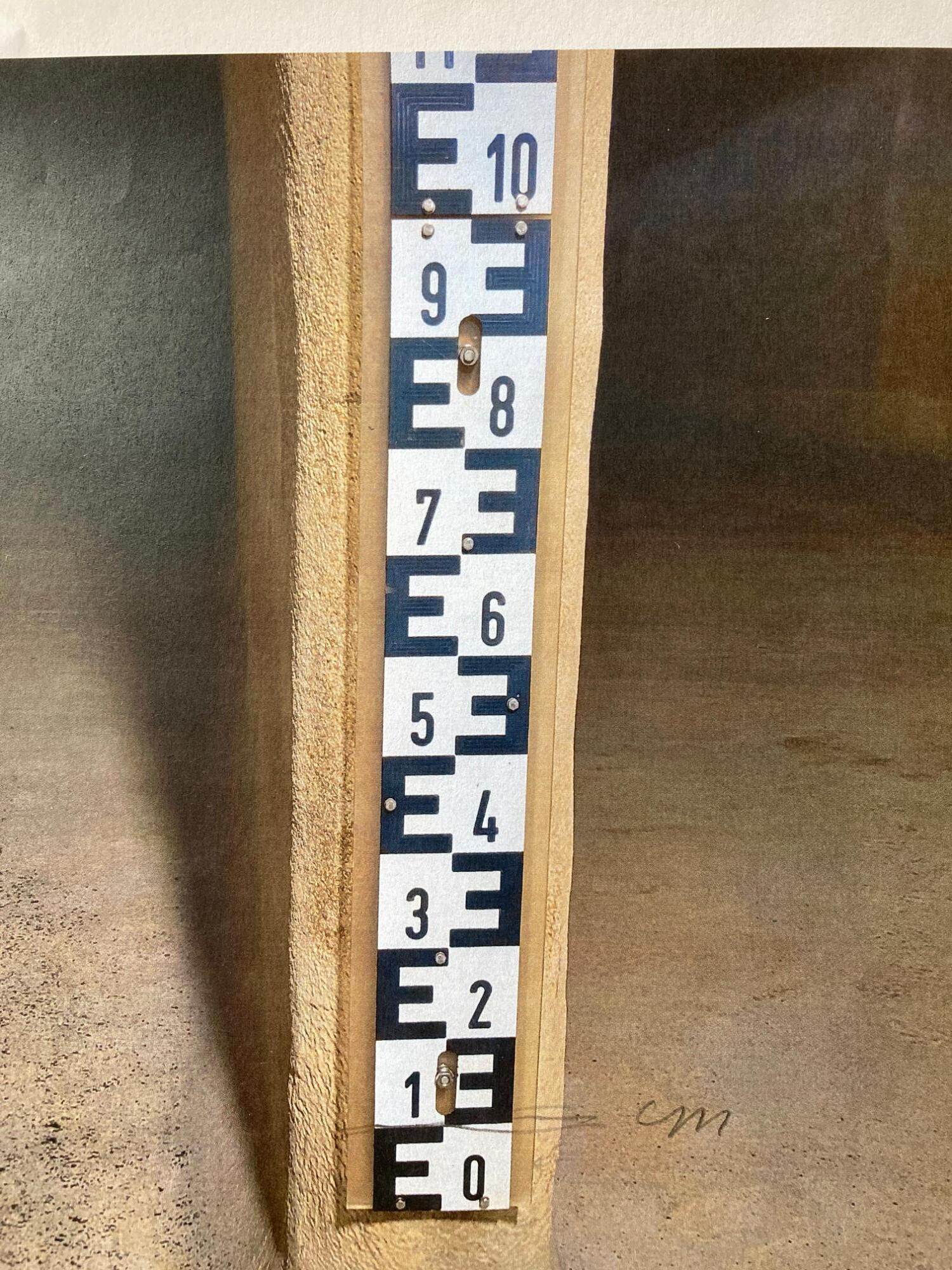
Pegellatte: Aus welcher Schrift stammen diese Zahlen?
Hallo. Für eine Ausstellung muss ich eine Pegellatte nachsetzen. Da die Latte im Kontext mit Bildern einer bestehenden Latte gezeigt wird, möchte ich unbedingt bei den Zahlen mit derselben Schrift arbeiten. Kann mir jemand sagen, wie diese Schrift heisst.
Danke, lieber Thomas. Ich bin eigentlich auch bei der DIN gelandet. Doch die "Endungen" der 6 und der 9 stimmen gar nicht überein und auch die "Abwärtsseite" der 1 scheint mir kürzer zu sein...
Es gibt in der DIN1451 für die 6 und 9 zwei verschiedene Formen. Mit Bogen und gerade. Die Latte hat die Formen mit Bogen. Bzgl. der 1 bin ich jetzt überfordert.
Ah, super, danke! Mit Bogen bei der 6 und der 9 ist das für mich so wunderbar und hat sich damit erledigt. Gruss und Dank.
Ansonsten hätte man noch fragen können, ob irgendwo der Hersteller ersichtlich ist. Diese Latten mit dem "E" erinnern mich stark an Nivellierlatten aus dem Vermessungsbereich und da gab es auch zwei bedeutende Schweizer Firmen, so dass man nach Schweizer "DINs" hätte suchen können ...